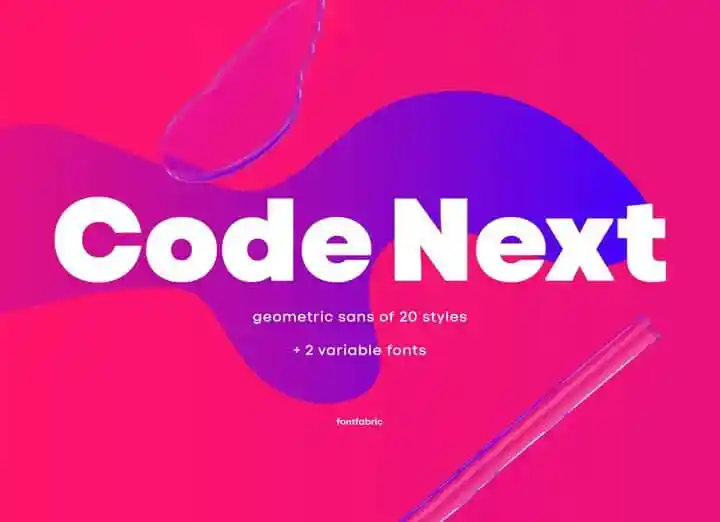
Code Next Sans Serif Font – Fonte Grátis
Code Next Sans Serif Font
A fonte Code Next Sans Serif é uma opção perfeita para designers buscando transparência, simplicidade e modernidade em seus projetos digitais. Desenhada pela Fontfabric, ela conta com uma grande variedade de pesos — 22 totalmente, composta por 11 linhas retas e 11 itálicas — abrangendo um range de tipografia que vai desde Hairline até Black. Esta fonte está projetada para atender qualquer aplicação moderna em impressão, web e visualização digital. O que torna a Code Next Sans Serif especialmente versátil são suas propriedades para multi-línguas, incluindo Latin Extendido, Cyrillic Extendido e grego. Isso significa que a fonte pode ser usada sem problemas nas mais diversas aplicações multilingues, desde materiais educacionais até comunicações globais. Seja em um projeto de design gráfico, site ou aplicativo mobile, a Code Next Sans Serif é uma excelente escolha para manter o estilo limpo e moderno que seu trabalho merece.